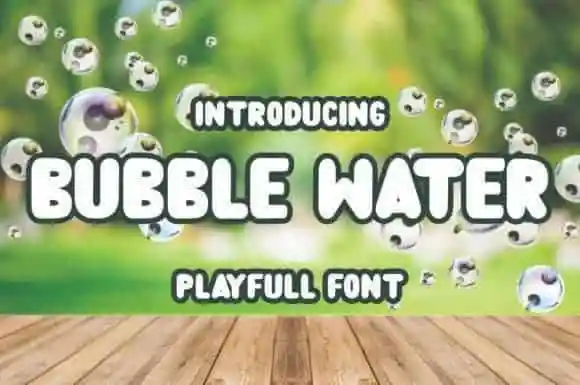
Bubble Water Display Font – Download Grátis
A Bubble Water Display Font é uma escolha perfeita para designers que buscam um estilo vibrante e natural para seus projetos. Essa fonte bold sans serif oferece tanto versões sólidas quanto lineárias, criada pelo font designer Savirafaeyzaart. Com seu charme suave e sua aparência amigável, esta fonte é uma ótima opção para design de ambientes como piscinas ou áreas aquáticas, destacando-se perfeitamente por conta de sua rica e única estética. Sem limitações em criatividade, a Bubble Water Display Font atende aos desejos mais audaciosos dos designers que buscam incorporar um toque único em seus projetos.